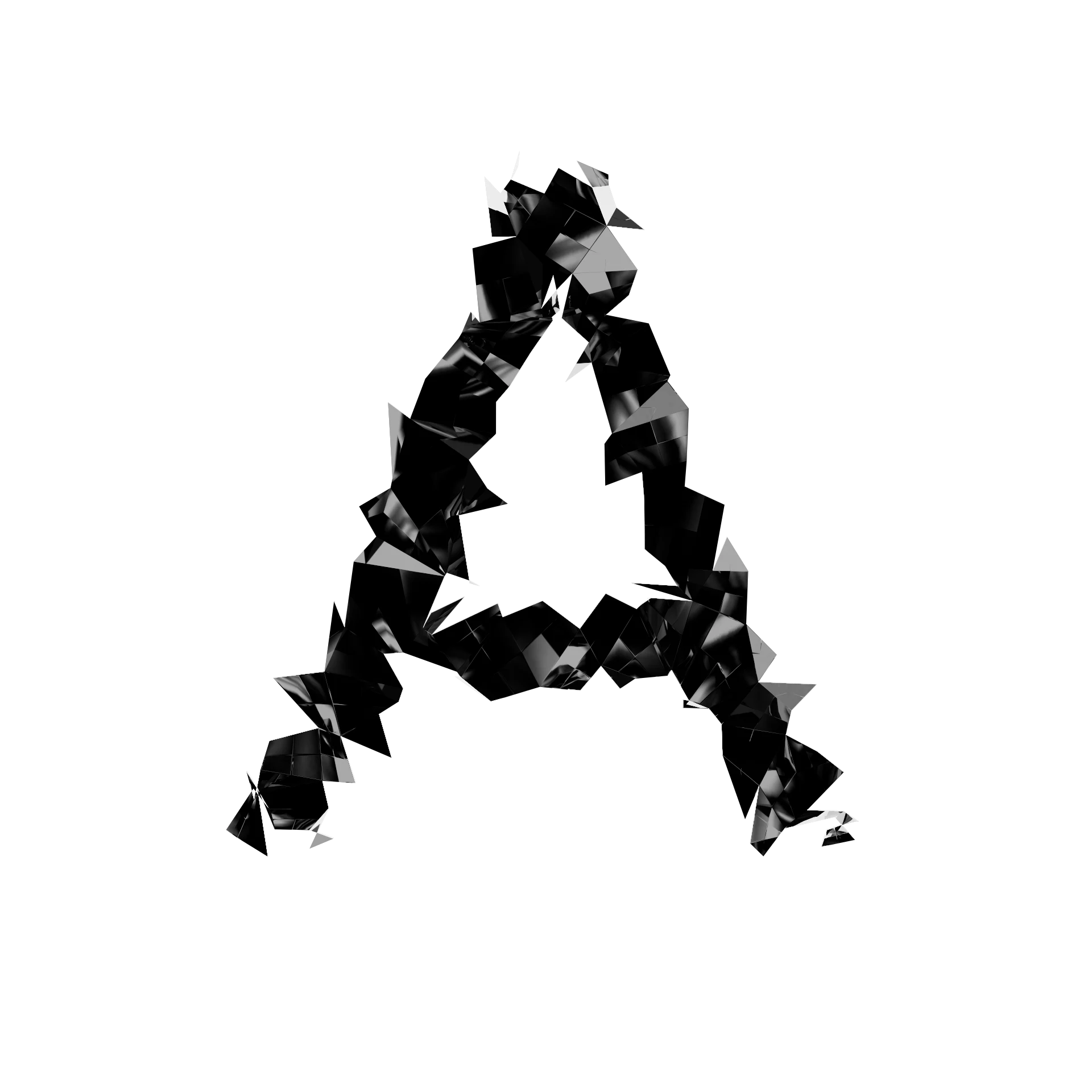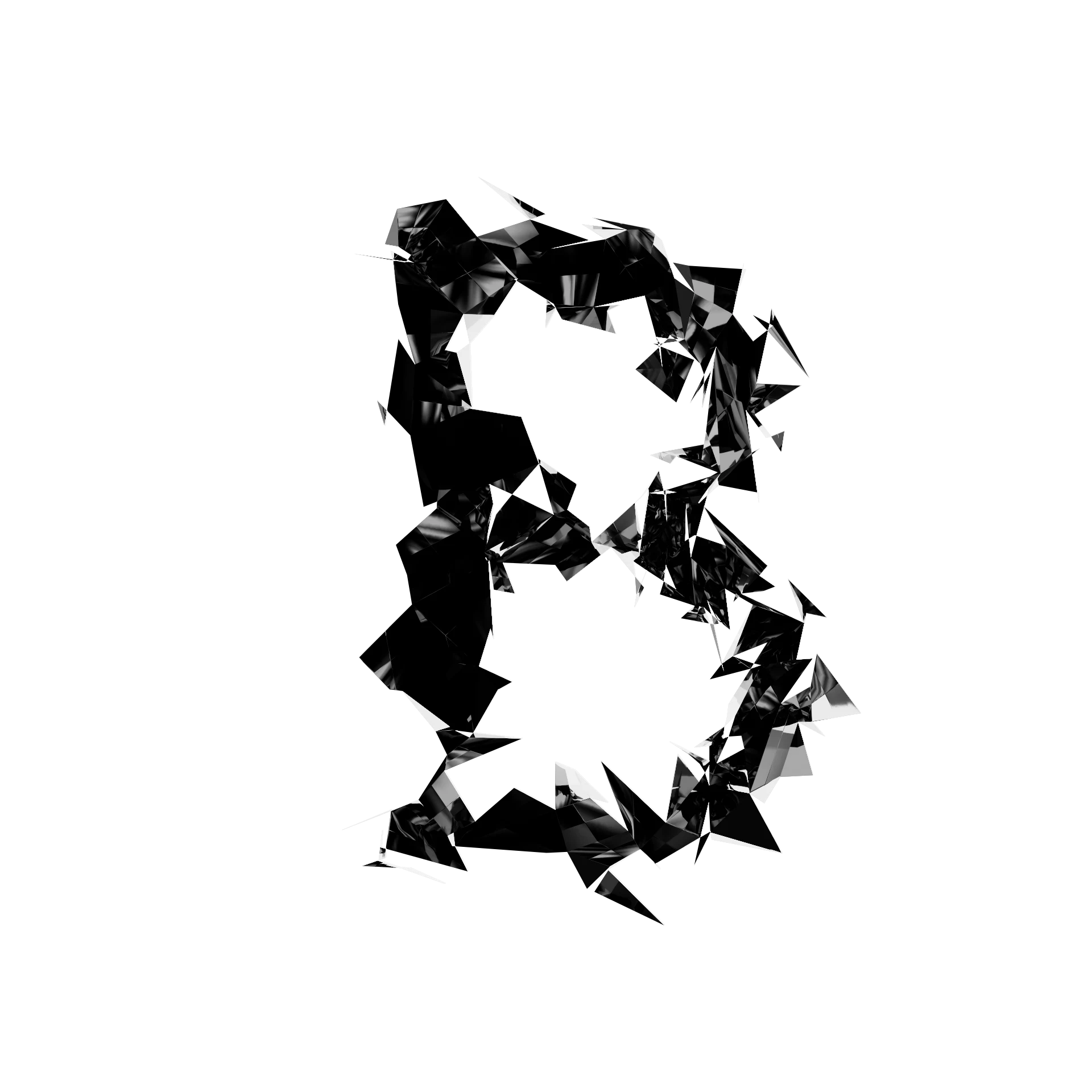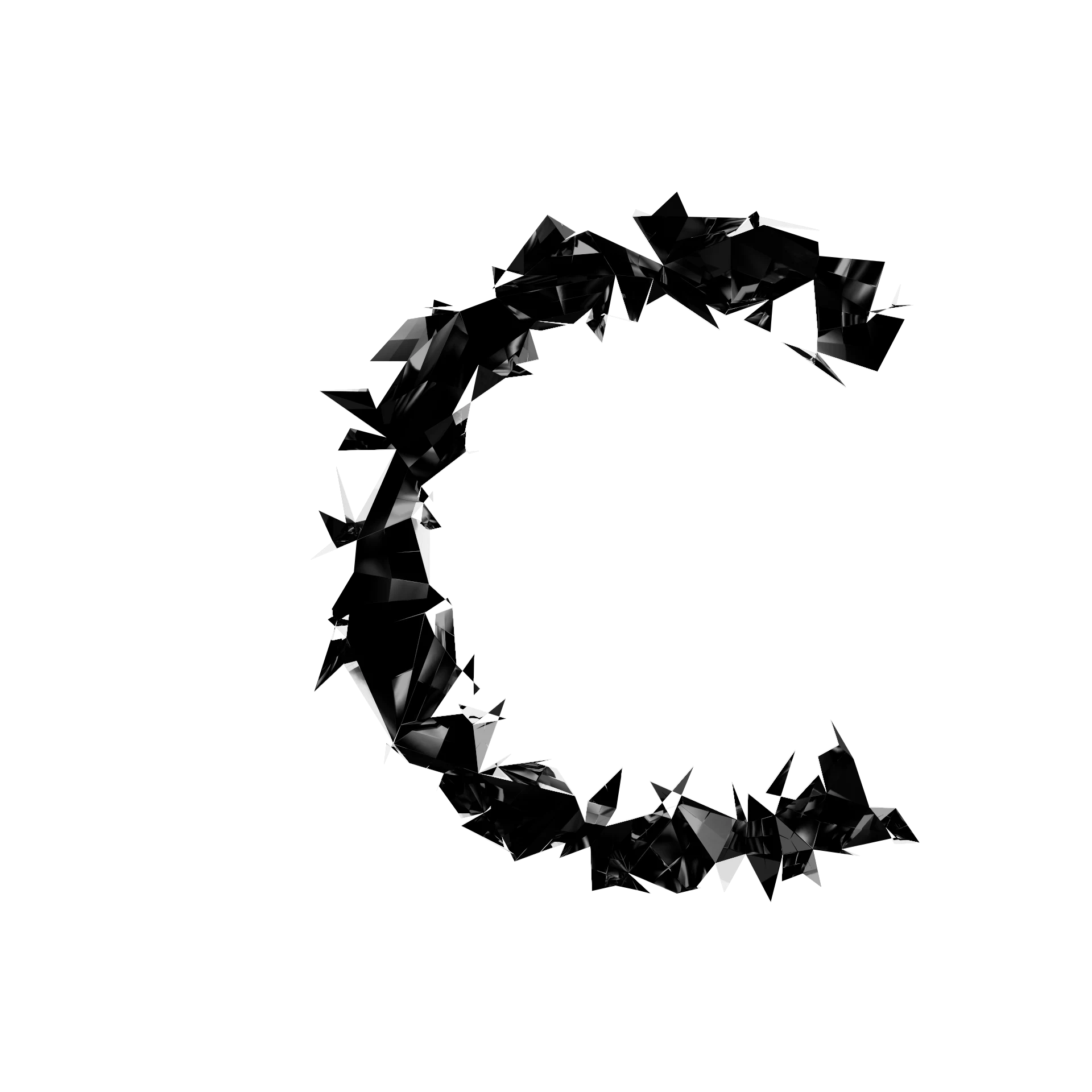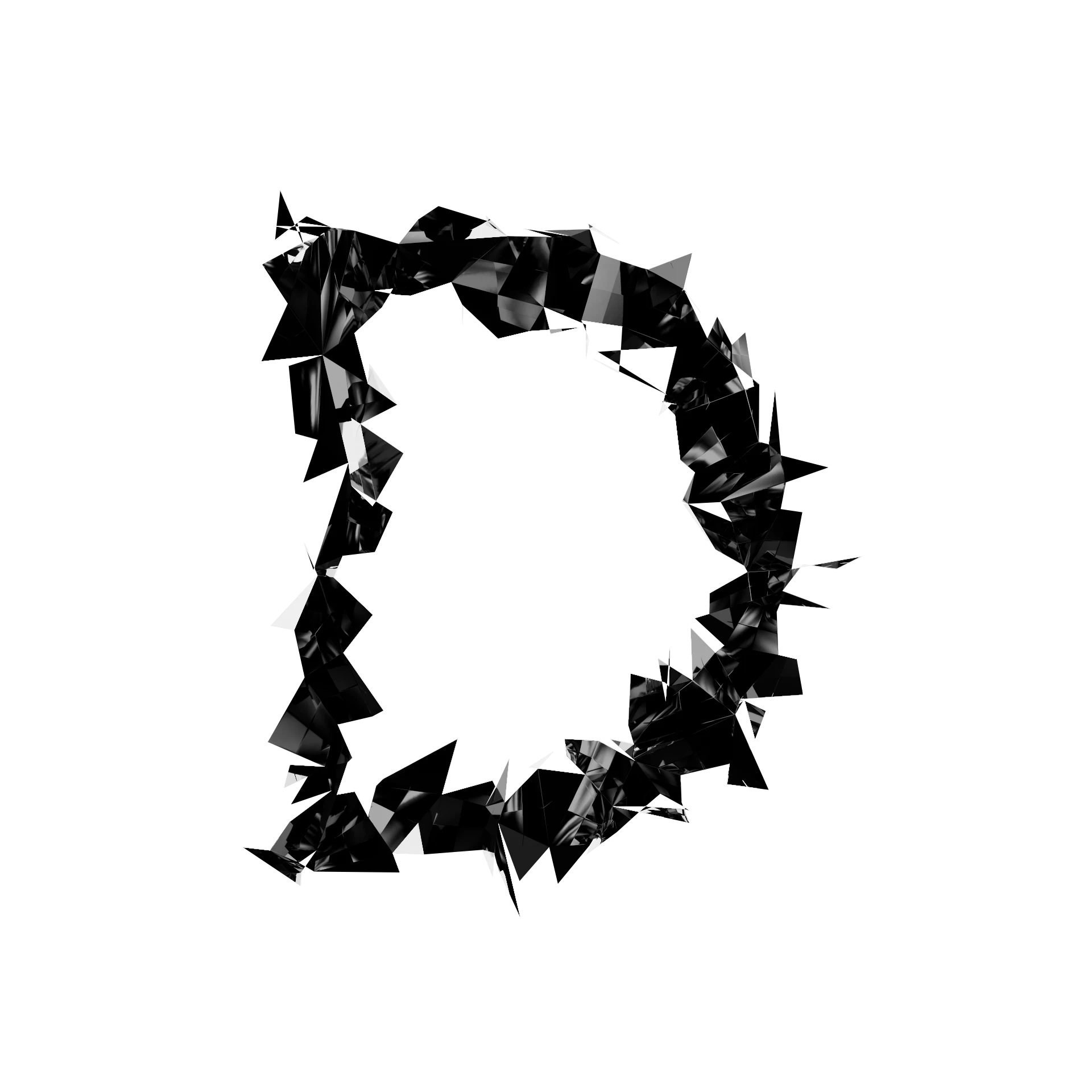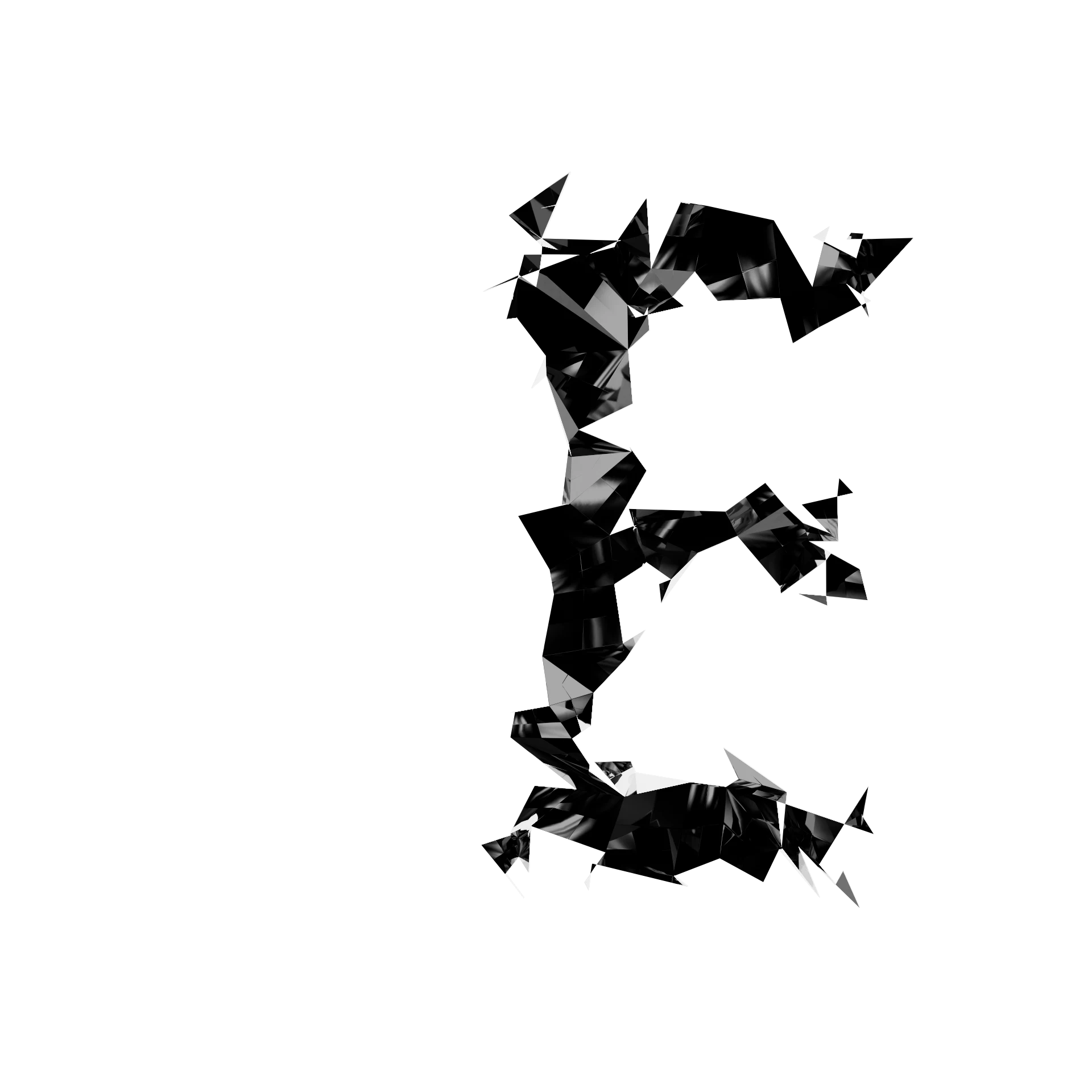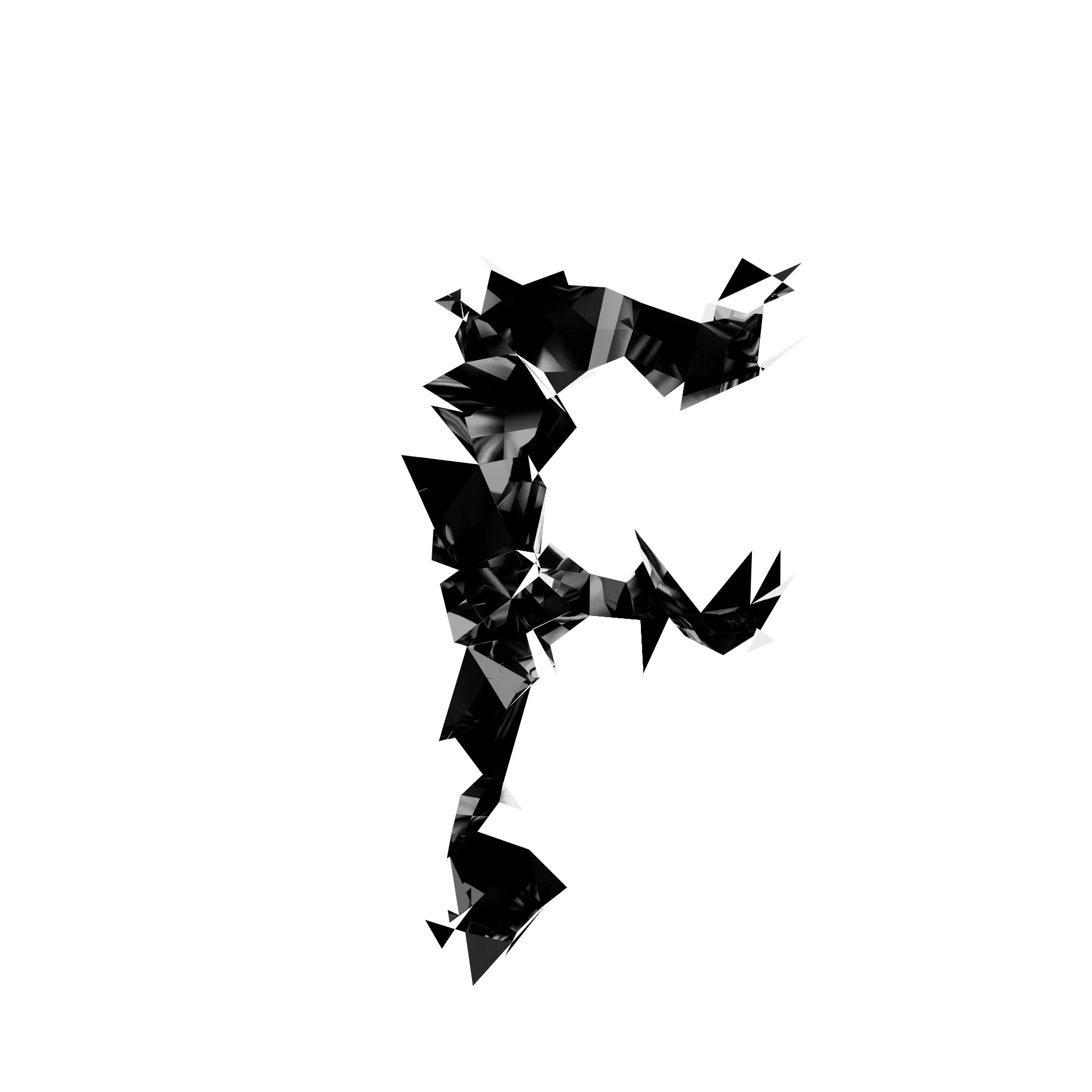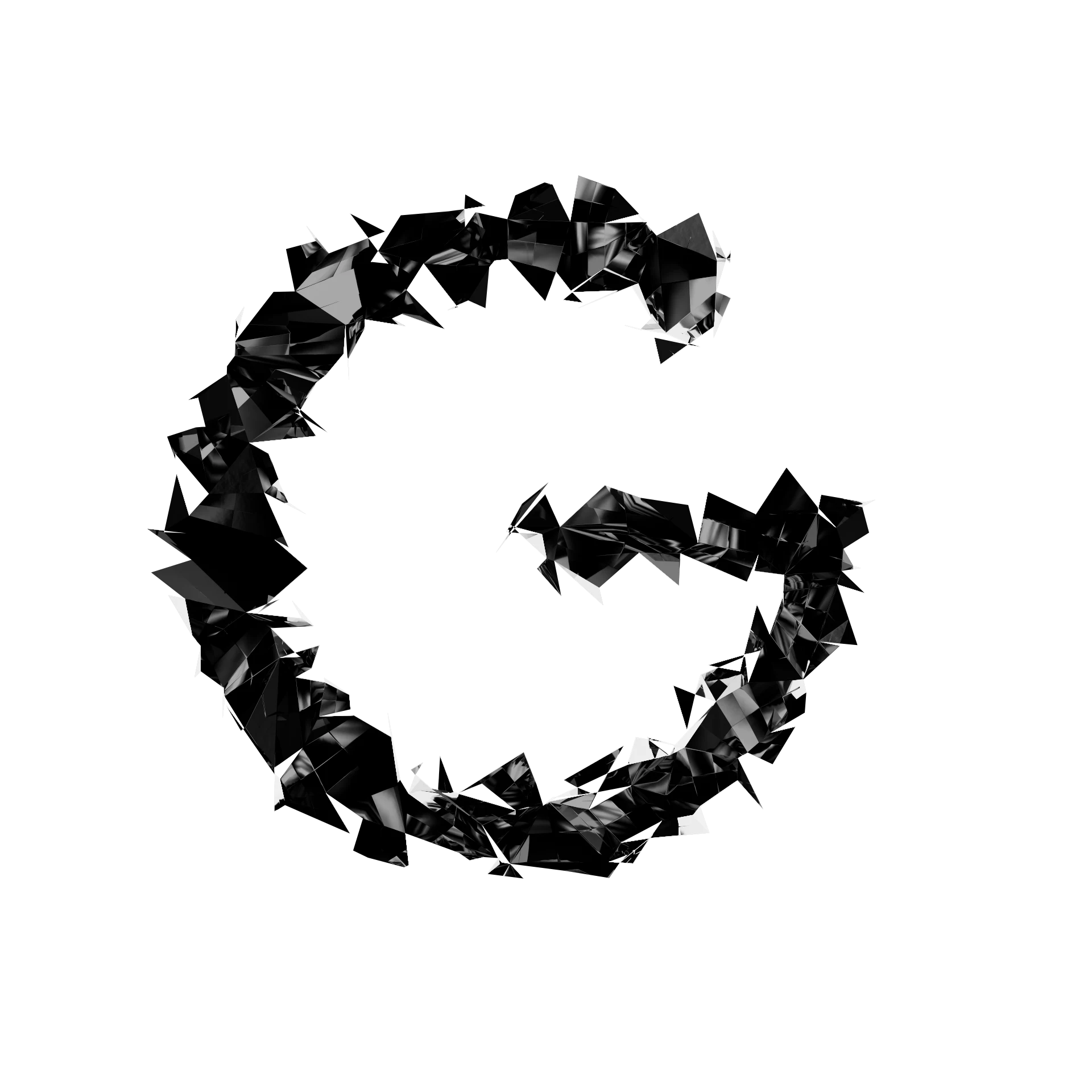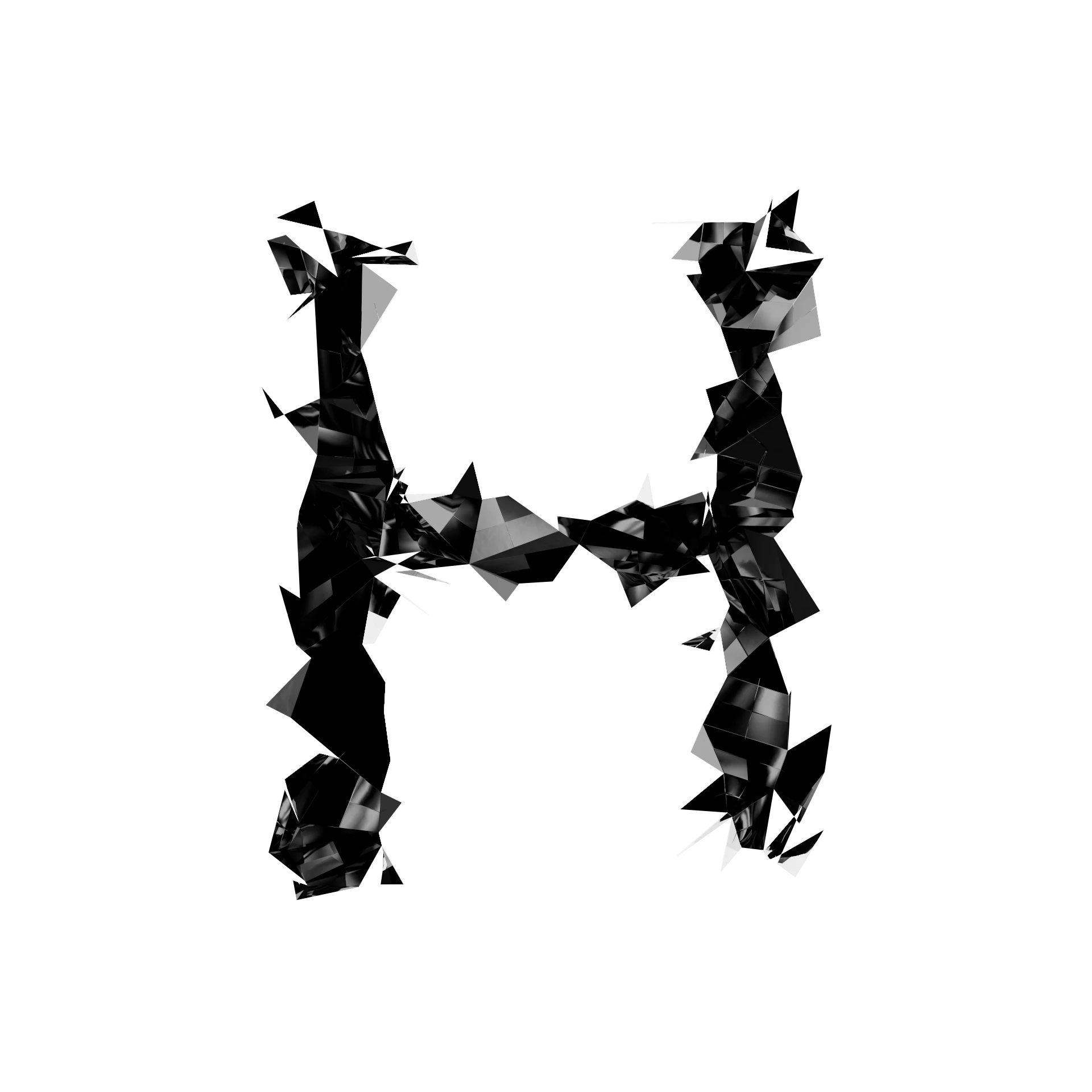
El alfabeto latino sometido a un sistema de fractura voronoi aplicado glifo a glifo. Cada carácter se extrude en tres dimensiones y se quiebra en esquirlas angulares de material especular negro; los 26 resultados se presentan sobre fondo blanco. La silueta original permanece reconocible en el agregado de piezas — la identidad de cada letra sobrevive a la destrucción de su masa continua.
La fractura como sistema constructivo: cada glifo del alfabeto latino se trata como un volumen sólido que se somete a un proceso de fragmentación voronoi. El interés no está en el impacto o la destrucción como metáfora, sino en comprobar si un conjunto de esquirlas angulares puede sostener la identidad de un carácter tipográfico. La respuesta que propone el proyecto es que sí — siempre que la distribución de masa respete el esqueleto original.
Cada letra se extrude desde su contorno vectorial a una profundidad uniforme. Sobre ese sólido se aplica un fracturador voronoi con semilla de ruido constante para toda la serie — garantizando que el tamaño y la orientación de las esquirlas sea comparable entre caracteres. El material especular negro con highlights blancos se asigna de forma idéntica a los 26 modelos.
Construcción del contorno vectorial por carácter → extrusión uniforme en Cinema 4D → aplicación del fracturador voronoi con parámetros fijos → asignación de material especular → iluminación de estudio (luz principal superior derecha, relleno sutil) → render sobre fondo blanco → exportación como PNG.